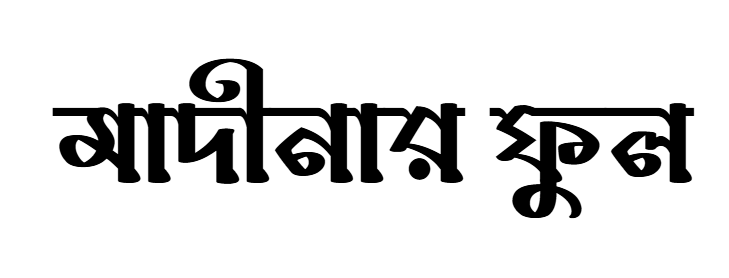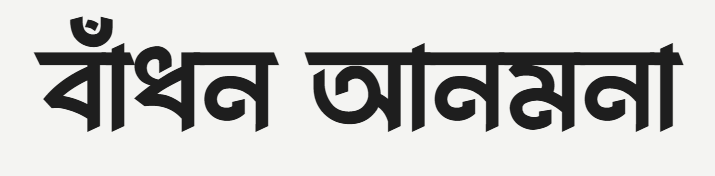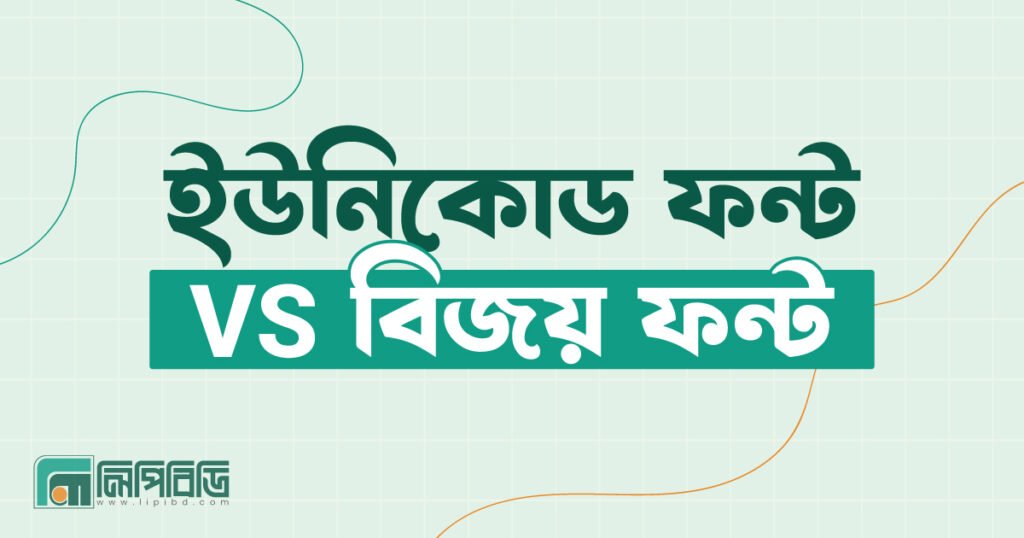
বাংলা লেখার জগতে সবচেয়ে বেশি বিভ্রান্তি তৈরি করে এই একটি প্রশ্ন
Unicode Bangla Font না Bijoy Font, কোনটা ব্যবহার করা ভালো?
অনেকেই এখনো Bijoy ব্যবহার করছেন অভ্যাসের কারণে, আবার নতুন ইউজাররা সরাসরি Unicode Bangla Font দিয়ে শুরু করছেন। কিন্তু এই দুই ধরনের ফন্ট আসলে এক না। এদের কাজের ধরন, compatibility, এবং ভবিষ্যৎ completely আলাদা।
চলুন সহজ ভাষায় পার্থক্যটা বুঝি।
Bijoy Font কী?
এখানে আপনি যা টাইপ করেন, সেটা আসলে standard Bangla নয়। Bijoy font/Ansi Font ব্যবহার করে লেখা text দেখতে Bangla হলেও ভিতরে ভিতরে সেটা Unicode না।
Bijoy Font সাধারণত ব্যবহার হয়:
- পুরোনো অফিস ফাইল
- কিছু সরকারি ডকুমেন্ট
- পুরোনো print workflow
সমস্যা হলো:
- Bijoy লেখা copy–paste করলে ভেঙে যায়
- Website বা mobile-এ ঠিকমতো দেখায় না
- Google, Facebook, modern apps ঠিকভাবে read করতে পারে না
Bijoy এখন মূলত legacy system।
Unicode Bangla Font কী?
Unicode Bangla Font হলো আন্তর্জাতিক Unicode standard অনুসরণ করে তৈরি Bangla font।
এখানে যা লেখা হয়, সেটা universally readable।
Unicode Bangla Font ব্যবহার করলে:
- সব device-এ লেখা ঠিকভাবে দেখা যায়
- Website, mobile, software সব জায়গায় support করে
- Google সহজে index করতে পারে
- Copy–paste করলে লেখা নষ্ট হয় না
আজকের দিনে modern Bangla typing, blogging, social media, এবং web content-এর জন্য Unicode Bangla Font standard হয়ে গেছে।
মূল পার্থক্য এক লাইনে
- Bijoy Font = পুরোনো system, limited compatibility
- Unicode Bangla Font = modern standard, future-proof
এই কারণেই এখন প্রশ্নটা শুধু preference না
প্রশ্নটা হলো আজকের দিনে কোনটা ব্যবহার করা বুদ্ধিমানের কাজ?
কোন ক্ষেত্রে Bijoy এখনো ব্যবহার হয়
সত্য কথা বললে, Bijoy Font এখন আর mainstream নয়, কিন্তু কিছু নির্দিষ্ট ক্ষেত্রে এখনো এটি ব্যবহার করা হয়। কারণ এগুলো মূলত পুরোনো workflow এবং অভ্যাসের সাথে জড়িত।
নিচে বাস্তব কারণগুলো দেওয়া হলো।
1. পুরোনো সরকারি ও অফিস ডকুমেন্ট
অনেক সরকারি অফিস, শিক্ষা প্রতিষ্ঠান এবং প্রিন্টিং হাউসে এখনো পুরোনো Bangla document archive আছে যেগুলো Bijoy Font-এ লেখা।
এই ফাইলগুলো:
- ৫–১০ বছর আগে তৈরি
- Bijoy encoding-এ সংরক্ষিত
- নতুন করে convert করা হয়নি
এই ডকুমেন্ট edit বা update করার সময় এখনো Bijoy ব্যবহার করা হয়, কারণ Unicode-এ convert করলে layout বা spacing ভেঙে যেতে পারে।
2. Legacy Printing Workflow
কিছু পুরোনো printing press এখনো Bijoy-based workflow ব্যবহার করে।
কারণ:
- পুরোনো software setup
- Trained operator শুধু Bijoy জানে
- Template ও layout আগে থেকেই Bijoy-এ তৈরি
বিশেষ করে local newspaper, book printing, বা notice printing-এ এই প্রবণতা দেখা যায়।
3. অভ্যাসগত ব্যবহার
অনেক ব্যবহারকারী শুধু একটাই কারণে Bijoy ছাড়তে চান না
অভ্যাস।
- বছরের পর বছর Bijoy keyboard layout ব্যবহার
- Blind typing speed ভালো
- Unicode শেখার সময় দিতে চান না
এই কারণে কিছু senior typist এখনো Bijoy ব্যবহার করেন, যদিও modern alternatives আছে।
4. পুরোনো Software Compatibility
কিছু পুরোনো desktop software বা DOS-based system এখনো Unicode support করে না।
এই software গুলোতে:
- Bangla text support সীমিত
- Bijoy ছাড়া অন্য option নেই
এই ক্ষেত্রে বাধ্য হয়ে Bijoy ব্যবহার করা হয়।
5. Short-Term Offline কাজ
কিছু ক্ষেত্রে শুধুমাত্র:
- Offline typing
- Print-only document
- Copy–paste দরকার নেই
এমন কাজ হলে কিছু মানুষ এখনো Bijoy ব্যবহার করে, কারণ তাদের কাজ সেখানেই শেষ।
৫টি সেরা Unicode Bangla Font
1. Bhasha Rekha
Bhasha Rekha একটি bold, clean এবং modern Unicode Bangla font।
এটা poster design-এ use করলে headline & title অংশে খুব শক্ত presence দেয়। সাধারণ typography ধরনের Bangla ফন্টের তুলনায় এই ফন্টে strokes একটু বেশি টেকদি tone আছে, তাই দূর থেকে পড়া যায় সহজেই।
Why it’s useful:
- Poster headline, offer banner
- Social media title
- Announcement poster
Design Tip:
Large text size-এ এই ফন্টের round edge ও straight line balance ঠিক থেকে readability বাড়ায়।
2. Agnirekha
Agnirekha অতটা classic না, contemporary Bangla font বলা যায়। এই ফন্টে রয়েছে একটু artistic stroke এবং visual impact, যা design-এ crispy look দেয়। Poster design-এ শিরোনাম বা tag line এখানে ভালো লাগে।
Why it’s useful:
- Poster main headline
- Catchy banner text
- Creative stage promotion poster
Design Tip:
Agnirekha-র style কিছুটা energetic, তাই monochrome poster এ black-white contrast-এ খুব ভালো দেখায়।
3. Mahfuj Cirkot Font
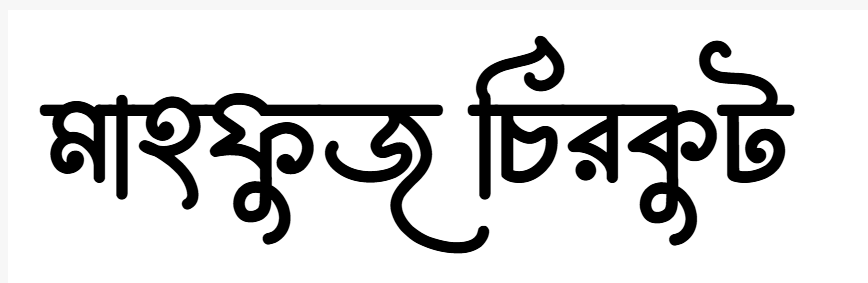
Mahfuj Cirkot একদম decorative ও playful Unicode Bangla font। এই ফন্ট এ poster-এ ব্যক্তিগত বা cultural design look পেতে চাইলে perfect। এর letter shape-এ light artistic twist আছে যা creative design-কে elevate করে।
Why it’s useful:
- Cultural events
- Art-themed posters
- Festival banners
Design Tip:
আর্টিস্টিক posters-এ subtitle-এর নিচে small decorative line add করলে visual harmony বাড়ে।
4. Niribili Plain Version
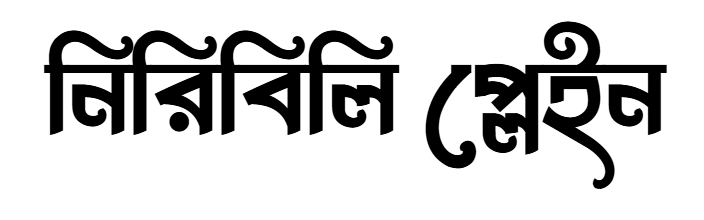
Niribili Plain Version হলো smooth, minimalistic এবং very readable Unicode Bangla font। Classic poster design-এ যেটা চান, ঠিক সেই type-এর font।
Simple headline এবং sub-text হিসেবে equally effective, যেটা poster design-এ balance তৈরি করে।
4) Mamun Masud Font
Mamun Masud আরেকটি Bijoy style Bengali font যার strokes elegant and classic. এটি headline বা title text-এ decent appearance দেয়, বিশেষ করে print posters বা desktop design-এ।
Best Use:
- Print headline
- Poster headline
- Decorative banners
Drawbacks:
- PixelLab, Canva mobile, Web text-এ support নেই
- Copy paste issue
Pro tip:
Graphic design purpose-এ PNG export করে use করা safe option, otherwise avoid as editable text.